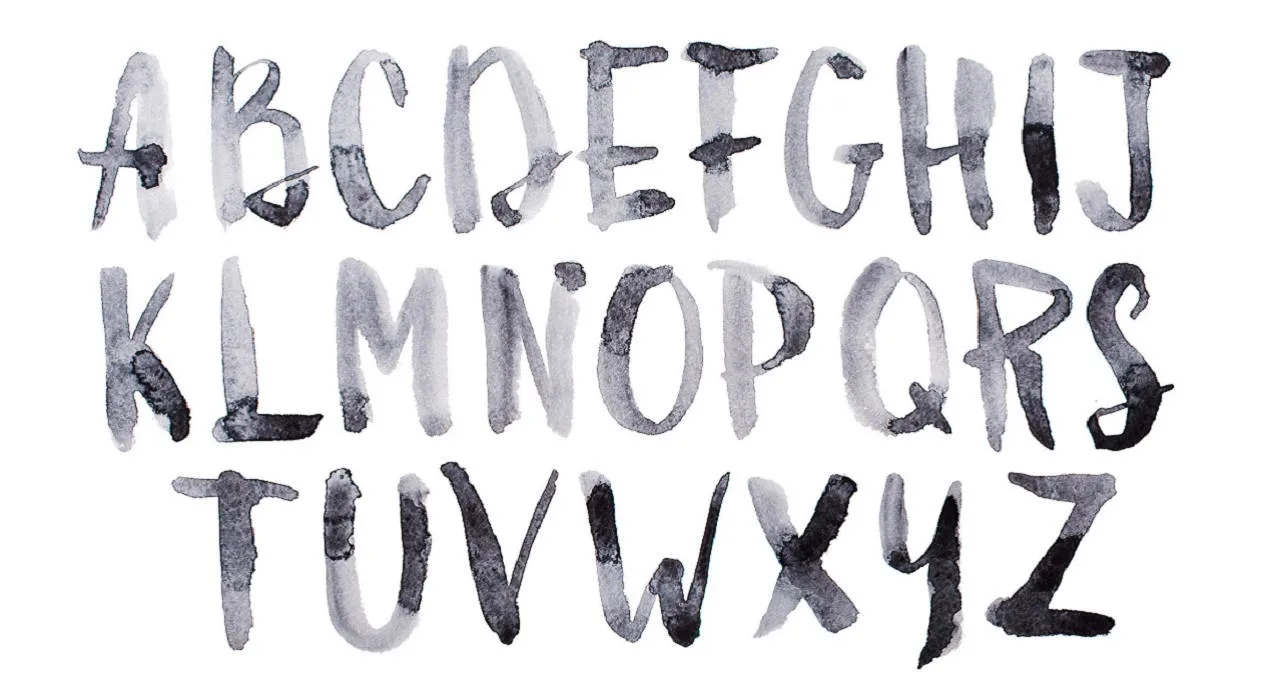
Ci sono molti elementi da tenere in considerazione quando scegliamo il font per il nostro prossimo progetto. In particolar modo c’è da tenere in considerazione il target di riferimento e a quale generazione appartiene tale target. Sì, perché le varie generazioni hanno gusti molto diversi, anche in fatto di carattere tipografico. Ecco i font preferiti dalle diverse generazioni.
I font preferiti dai Millenials
I Millenials sono la generazione più particolare in assoluto. Innanzitutto, la loro particolarità principale è il fatto di essere cresciuti a cavallo con la digitalizzazione.
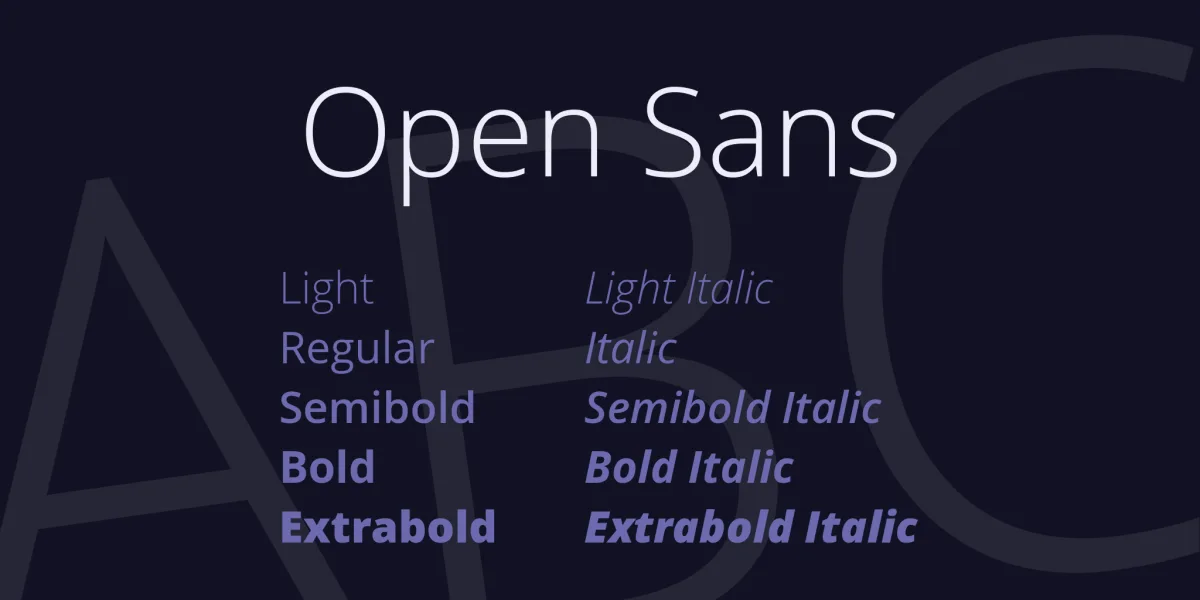
Loro c’erano quando ancora si giocava in giardino, quando ci si chiamava dal telefono fisso e ci si incontrava al muretto della piazza. Ma c’erano anche quando i computer hanno invaso le nostre case, quando Internet è nato, quando la tecnologia e il mondo digitale sono iniziati a diventare una parte integrante e fondamentale delle nostre vite. E proprio per la loro presenza durante questo delicato passaggio tecnologico, i Millenials altro non sono che i veri e propri nativi digitali.
Ma non è tutto. I Millenials sono anche quella generazione che hanno attraversato le crisi più profonde. Ed è per tutti questi motivi (e forse anche per altri) che i Millenials sono quella generazione che più di tutti danno importanza al font.
Se il tuo target è questa generazione devi fare molta attenzione, perché se un Millenial crede che quel font stoni profondamente con il messaggio, l’intera figura aziendale crollerà come un castello di carte.
Quindi quali font dobbiamo scegliere? In generale preferiscono i font chiari e leggibili, ma che non nascondono un pizzico di personalità scoppiettante, come Open Sans, Montserrat, Poppins o Raleway.
La generazione X
Facciamo un passo indietro, perché anche la Generazione X ha vissuto l’avvento del digitale. Tuttavia, lo ha vissuto in maniera molto diversa, perché quando il boom tecnologico è esploso loro erano già un po’ più grandicelli rispetto ai Millenials.
Tuttavia, anche per loro il font è una cosa seria, ma lo sono anche le radici, le tradizioni e quel retrogusto che rende tutto ciò che “c’era una volta” molto meglio di ciò che è moderno.
Questo loro stile di vita molto nostalgico li porta a preferire font molto classici Arial, Franklin Gothic, Futura, Garamond, Times New Roman, ma in particolar modo, secondo alcune ricerche, sembra che questa generazione prediliga tra tutti l’Helvetica!
I font preferiti dalla generazione Z
Abbiamo visto come le generazioni che hanno vissuto la digitalizzazione diano davvero molta importanza alla scelta del giusto font. Questo potrebbe farci pensare che le generazioni più giovane non diano tanta importanza a ciò, ma ci sbagliamo! In realtà anche la generazione Z apprezza la ricerca e lo studio che si può celare dietro la scelta del font giusto.
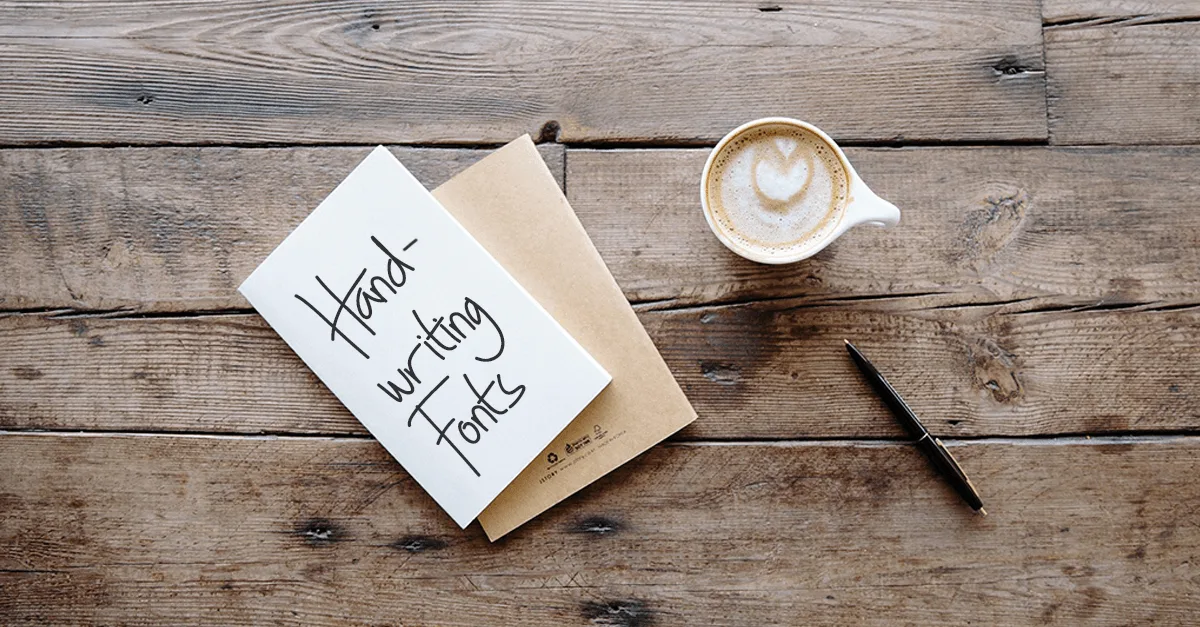
Ma dobbiamo considerare che questa è la generazione dei social e perciò qualsiasi cosa gira intorno a questo mondo. La generazione Z ha ammesso che il font sbagliato può portarli a scartare subito un post.
Questa generazione adora i font hand written e quelli brush script. Ma anche font retrò futuristici, come Strelka, Keiko Titling.
Amano i font più particolari e sfrenati, abbandonando il pensiero less is more e abbracciando quello “too much is better”!